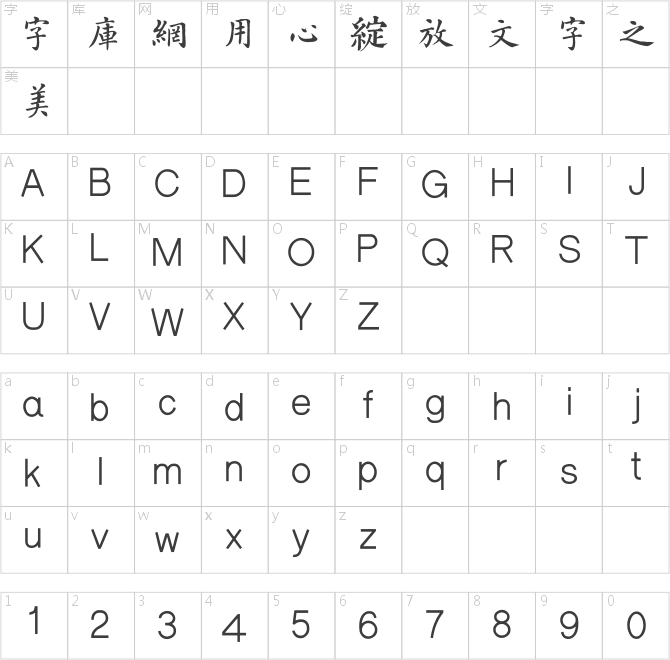
邯鄲潘齡皋千字文 詳情頁
字體名稱: 邯鄲潘齡皋千字
邯鄲潘齡皋千字文字體下載邯鄲(清)潘齡皋千字文
潘齡皋(1867年2月6日—1954年6月19日),字錫九,河北安新人。1881年,15歲的潘齡皋考中秀才,清光緒二十年(1894年)中舉人,后殿試中進士,授翰林院編修,曾先后在甘肅任知縣.知州.知府。
邯鄲潘齡皋千字文字體邯鄲(清)潘齡皋千字文字庫是一款讓人賞心悅目、百看不厭的中文字體,適合各類廣告和產品包裝設計應用,字體大小6.38MB,格式為ttf字體,上傳用戶是邯鄲字庫,作者/版權方為韓紹杰